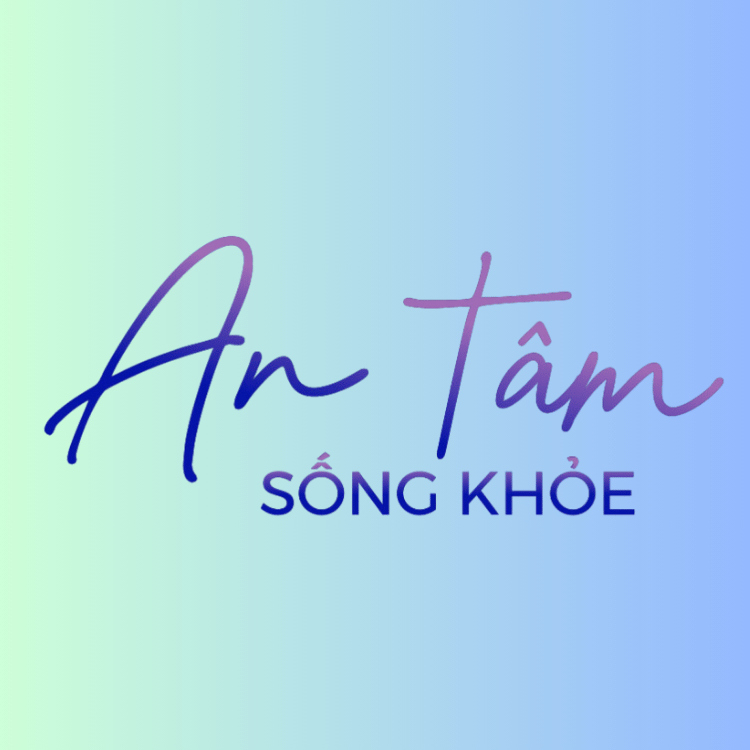
Giới thiệu về Font Việt hóa VIP Hevantica , Font thiệp cưới
Trong lĩnh vực thiết kế đồ họa chuyên nghiệp, việc lựa chọn một bộ Font Miễn Phí chất lượng luôn là ưu tiên hàng đầu của các designer. Đặc biệt, dòng Font Việt hóa VIP Hevantica , Font thiệp cưới đang trở thành lựa chọn hoàn hảo nhờ sự kết hợp tinh tế giữa nét chữ hiện đại và sự mềm mại đầy cảm xúc. Bộ font này không chỉ hỗ trợ đầy đủ bảng mã tiếng Việt mà còn mang lại trải nghiệm thị giác ấn tượng cho người xem.
Tại sao nên chọn Font Việt hóa VIP Hevantica cho thiệp cưới?
Với các sự kiện trọng đại, sự thanh lịch là yếu tố không thể thiếu. Font thiệp cưới Hevantica sở hữu các đường nét thanh mảnh, uốn lượn tự nhiên, giúp các mẫu thư mời trở nên sang trọng và đẳng cấp hơn. Điểm mạnh của bộ font này chính là sự đa dạng trong các biến thể, cho phép người dùng tùy chỉnh linh hoạt từ tiêu đề chính đến các đoạn nội dung chi tiết. Bạn có thể dễ dàng tạo ra những sản phẩm in ấn mang đậm dấu ấn cá nhân mà không lo lỗi font.
Ứng dụng thực tế của bộ font trong thiết kế hiện nay
Bên cạnh việc dùng làm Font thiệp cưới, bộ chữ này còn được ứng dụng rộng rãi trong thiết kế logo, bìa sách và các ấn phẩm quảng cáo cao cấp. Khả năng hiển thị sắc nét trên cả màn hình kỹ thuật số và bản in giúp Font Việt hóa VIP Hevantica giữ vững vị thế trong lòng người dùng. Đối với những ai đang tìm kiếm sự sáng tạo mới mẻ, đây chắc chắn là một công cụ không thể bỏ qua để nâng tầm tác phẩm thiết kế của mình.
Hướng dẫn sử dụng hiệu quả
- Kết hợp với các tông màu pastel để tăng vẻ lãng mạn cho thiệp.
- Sử dụng kích thước chữ lớn cho tiêu đề để tạo điểm nhấn thị giác.
- Kiểm tra khoảng cách ký tự để đảm bảo độ dễ đọc tốt nhất.